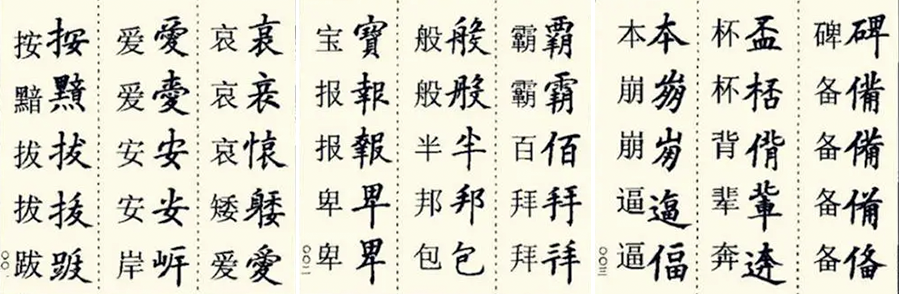
异体字是指与国家规定的正体字(标准字体)字音和字义相同,但字形不同的一组字。例如,“吴”是正体字,“吳”和“呉”是异体字。异体字并不等同于繁体字,它是一个字的正体之外的写法,由于汉字是由意符(表示整字意义的字符)、音符(表示整字读音的字符。)和记号(汉字中除去意符和音符后剩下的结构单位)所组成的,意符选取的角度因人而异,音符又不同于拼音文字中的字母,所以一字多形的现象在汉字的历史上很常见。